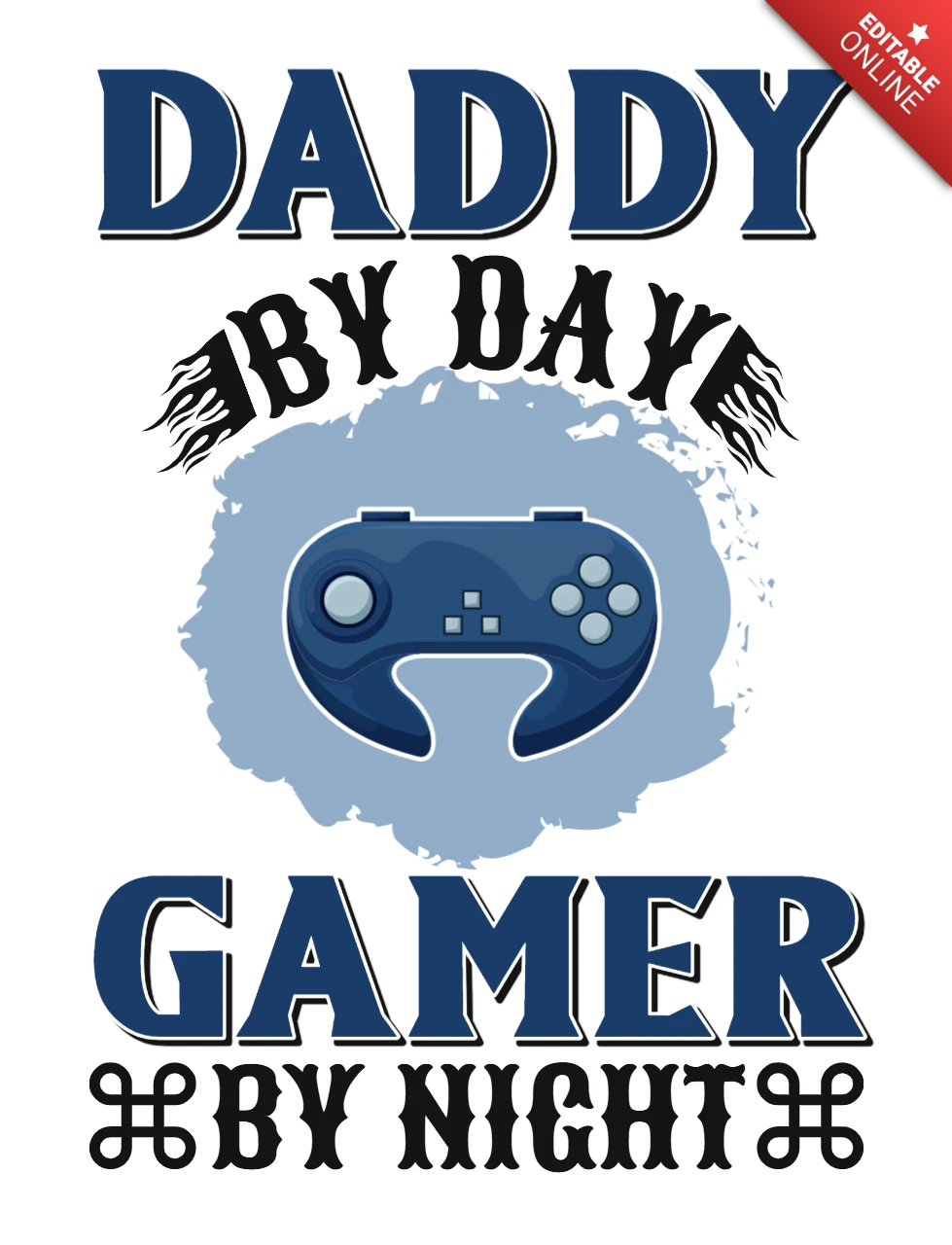
Modèle de design éditable pour le père d'un joueur avec une typographie audacieuse et un graphique de contrôleur
Éditer dans Design Studio Télécharger en JPGCélébrez la fête des pères avec notre modèle de conception ludique et modifiable, doté d'une typographie audacieuse et de thèmes de jeux nostalgiques - parfait pour le père qui aime s'amuser et sa console d'époque !